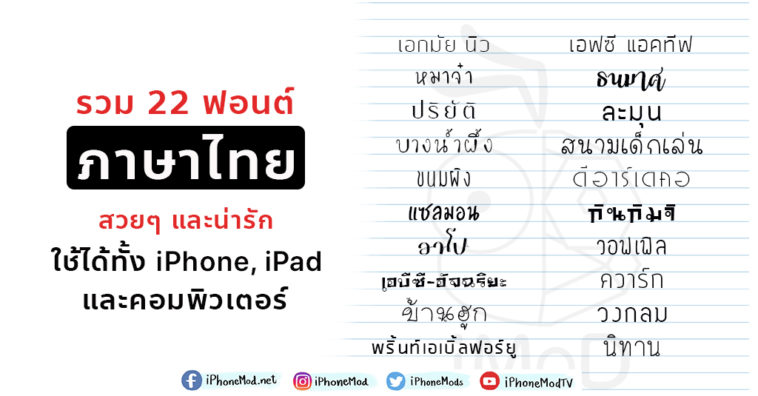
รวม 22 ฟอนต์ภาษาไทยสวยๆ และน่ารัก ใช้ได้ทั้ง iPhone, iPad และคอมพิวเตอร์
- เอกมัย นิว
- หมาจ๋า
- ปริยัติ
- บางน้ำผึ้ง
- ขนมผิง
- แซลมอน
- อาโป
- เอบีซี-อัจฉริยะ
- บ้านฮูก
- พริ้นท์เอเบิ้ลฟอร์ยู
- เอสบีฟ้อนต์
- เอฟซี แอคทีฟ
- ธนมาศ
- ละมุน
- สนามเด็กเล่น
- ดีอาร์เดคอ
- กิมจิ
- วอฟเฟิล
- ควาร์ก
- วงกลม
- นิทาน
- เอฟซี รีเบล
ตัวอย่างฟอนต์ทั้ง 22 แบบ